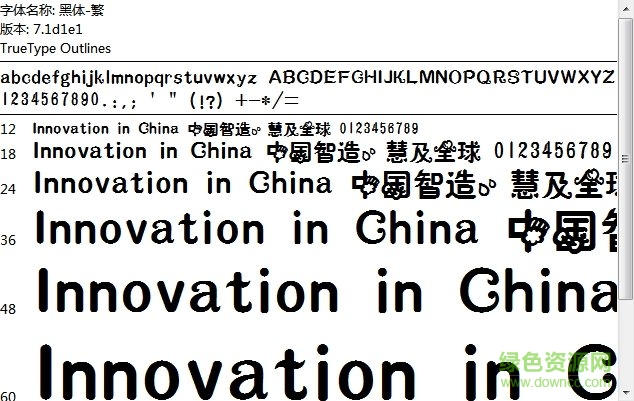
花花爱彩虹字体
花花爱彩虹ttf字体是一款有欧哲花朵、爱心、水滴等多种装修的卡通字体,整体十分Q萌活泼,支持日文、中文、韩文等多种输入,给大家带来更多样化的选择,绿色资源网今日推荐!
花花爱彩虹字体特色
花花爱彩虹采用了花纹风格,线条粗细适中,是一款适用于海报设计、广告图片设计等文字领域的艺术字体。字库完整,能满足大家的更多需要!
花花爱彩虹
花花爱彩虹体有着非常多的可爱点缀,兼具pop字体海报字体的特色,给人十分欢唱的视觉体验,文字更加生动有活力。